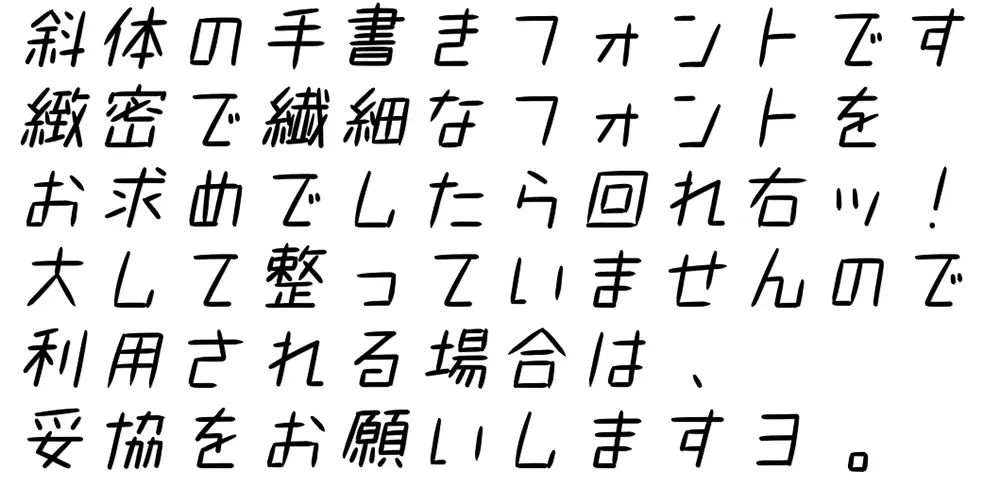
851斜書體(851テガキカクット)是由日本設計師 8:51:22 pm設計的一款手寫意大利斜體風格日文字體,當前字符數:4964個字符(不包括空格)
對應文字:平假名、片假名、拉丁文字(英語)、數字、符號(少許)、漢字(常用漢字+2200字左右)
注意:這款字體適用於繁體和日文,不適用於簡體中文,容易缺字。